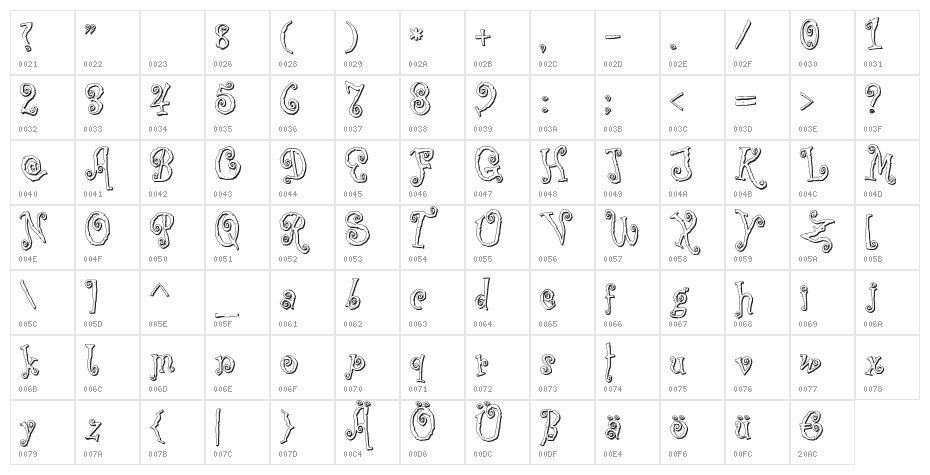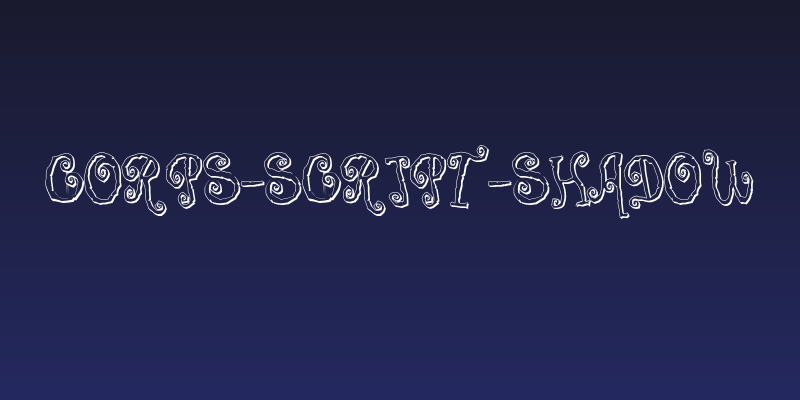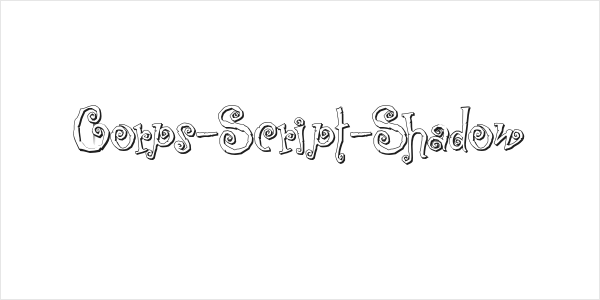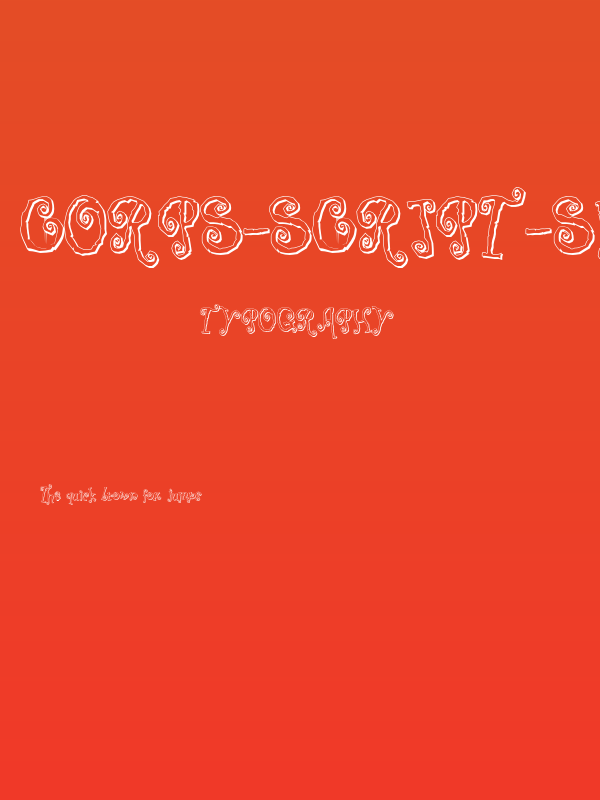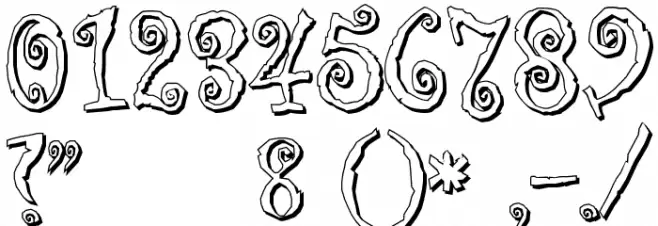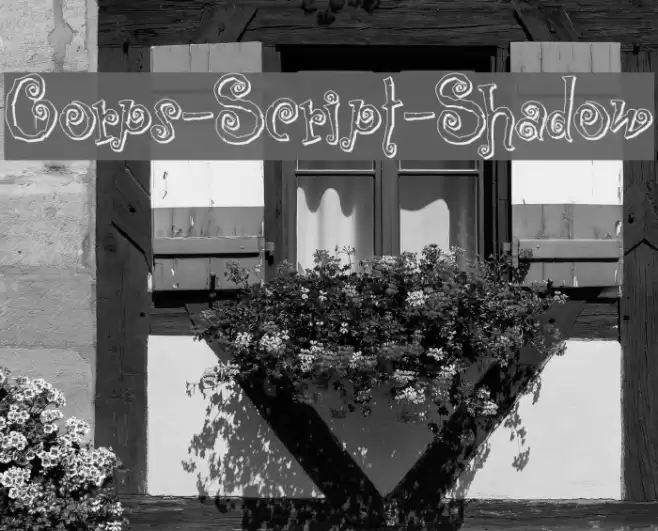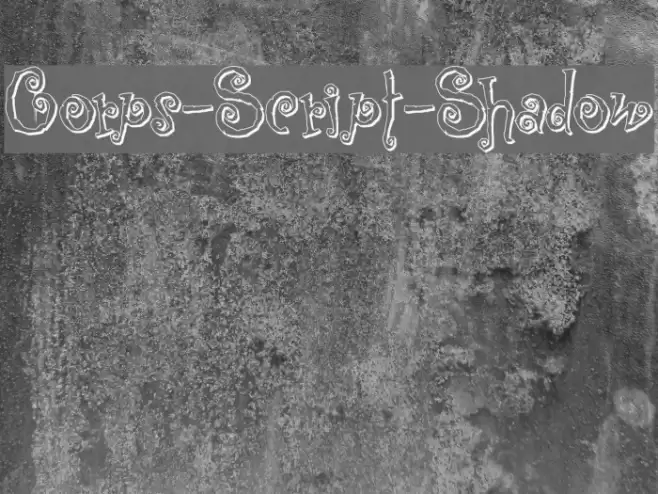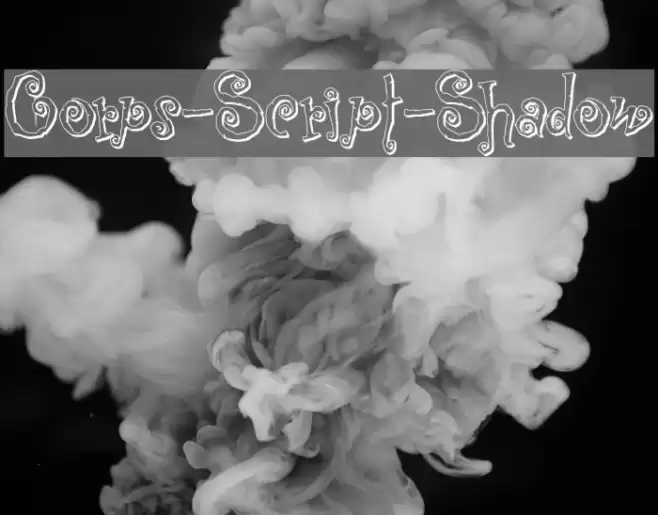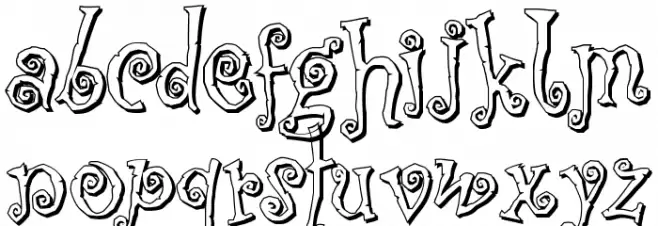
Corps-Script-Shadow Font
| Anwendungsfall | Headlines, Decorative text, Artistic projects |
| Vorgeschlagene Projekte | Ideal for children's book covers, playful invitations, creative posters, and artistic branding. |